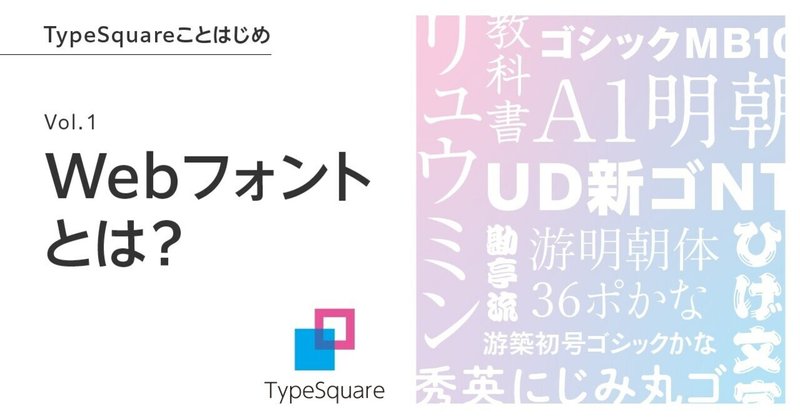
Webフォントとは? 「TypeSquare」ことはじめ
日々の情報収集やコミュニケーション、そしてショッピングや公的サービスの手続きなど、私たちの生活においてインターネットは必需品となりました。朝から晩までスマートフォンを見ていることも珍しくない今、Webサイトにおけるフォントは、サービスの印象や情報の伝わりやすさを決める要素として大きな役割を果たしています。
2021年、株式会社モリサワが提供するWebフォントサービス「TypeSquare」は、リリースから10年目を迎えました!そこでモリサワnote編集部では、もっとみなさんにWebフォントの素晴らしさを知っていただきたく、「TypeSquare」についてお伝えしていきたいと思います。
第1回目は自己紹介として、これまで日本語Webフォントが歩んできた道と、知っておいていただきたいことをご紹介します。
1.そもそもWebフォントって?
通常ウェブサイトは、パソコンやスマートフォンなどの端末へインストールされているデバイスフォントの中から、CSS(スタイルシートと呼ばれる、ウェブサイトの見た目を決める言語)で指定されたフォントを表示しています。
対してWebフォントは、サーバからフォントファイルを配信し、そのフォントを使ってウェブサイトを表示する仕組みになっています。つまり、指定されたフォントが端末にインストールされていなくても、デザイナーや開発者の指定する書体が表現できるのです。
2.Webフォントの歴史
1990年代後半、CSS2にウェブブラウザへのフォント自動ダウンロード、および一時的にアクティブ化を可能とする「@font-face」規則が導入されたことで、Webフォントの仕組みが完成しました。
しかし、当時はInternet Explorer4のみで使える、Microsoft社 独自仕様のフォントフォーマットEOT(Embedded OpenType)にしか対応できず、利用は限定的なものでした。
2000年代に入り、Firefox・Safari・Google Chromeなど、新しいウェブブラウザが次々と登場。TrueTypeやOpenTypeといった一般的なフォントフォーマットが「@ font-face」規則に対応できるようになりました。
これにより、欧米ではWebフォントの利用が増加!2000年代後半には、Typekit(現在のAdobe Fonts)やGoogle Web FontsなどのWebフォントサービスも登場し、どんどん普及が進みます。
そして、欧米より数年遅れをとることの2010年。ついに国内初の日本語対応Webフォントサービスが登場し、国内でもWebフォントサービスが少しずつ普及していきました。
3.日本語Webフォントが歩んできた道
では、10年目を迎える「TypeSquare」の進化とともに、日本語Webフォントがこれまで歩んできた道を振り返ってみましょう。
先ほど“欧米より数年遅れをとることの”とお伝えしたのには、日本語ならではの理由がありました。みなさんもお気づきかもしれませんが、日本語の書体は、漢字・ひらがな・カタカナと文字数が非常に多く、欧文書体に比べてデータサイズが数MBと格段に大きくなってしまうハンディがあります。
※ちなみに、モリサワフォントで提供している文字セットの最多収録文字数は『23,058文字』もあります!
よって、サービス開始当初の日本語Webフォントはデータサイズが大きく、ネットワークに負荷がかかり、ウェブサイトの表示に時間がかかってしまっていました。このタイムラグを解消するため、技術者たちは年々サービスを進化させます。
今では、表示に必要な文字だけをダウンロードする「ダイナミックサブセット」方式を利用し、配信するフォント自身の軽量化に成功!多くの場合、ファイルサイズは画像数枚分に収まるようになりました。
読み込み速度が向上したことで、通信速度が安定しない外出先やポケットWi-Fiなどの環境下でも、快適にウェブサイトを表示できます。現在では、更にデータサイズが小さくなった専用のフォントフォーマットWOFF(Web Open Font Format)で配信しているため、さらに表示速度が向上しました。
4.「TypeSquare」が得意なこと
ここからは、日本語Webフォント「TypeSquare」を利用するメリットをご紹介します。
■あらゆるニーズに応えます!豊富な書体ラインナップ
なんといっても、モリサワが提供する1,000書体を超えるフォントを、あらゆるデジタル端末で使えること!
一般的な明朝体やゴシック体はもちろん、デザイン書体や、かな書体、装飾書体、UD(ユニバーサルデザイン)書体に加え、欧文書体、中国語、韓国語など豊富な書体ラインナップを用意しています。多くの印刷物をはじめ、テレビのテロップやサイネージ、家電製品、ゲームなど、さまざまなシーンで利用されているモリサワフォントを、そのままウェブサイトでも使用可能。印刷物からデジタル端末まで、ブランドの世界観に一貫性を持たせられるのは魅力的ですよね。
では、Webフォントによってどれだけ印象が変わるのかを、実際に体験していただきましょう。
まずこのウェブサイトは、PCのデバイスフォントで表示させていますが、
全く同じデザインのウェブサイトをWebフォント(下は「解ミン 宙」)に変更すると、印象がガラッと変わります!
つまり、ウェブサイトの世界観を表現する上でも、書体選びはとても重要な役割を果たしているのです。
■ウェブサイトの制作・更新フローがラクに
これまでは、見出しやボタンの文字に好みの書体・効果を指定したい場合、画像を個別に作成していました。そのため、文字に変更があった場合は都度画像を作り直し、再度サーバへ上げなおす必要があったのです。
Webフォントなら使いたいフォントを指定して、通常のテキスト同様に文字サイズの調整やCSSによる効果を設定するだけでOK。急な文字修正が生じても、画像を作り直す手間が解消されます。
■拡大してもクリアで美しい文字
高解像度化が進むスマートフォンやタブレットでは、画像化された文字は画面をピンチアウトさせた際にぼやけて表示されることも。しかしWebフォントを使うことで、画面を拡大しても文字はクリアで美しさもキープ。ウェブサイトの仕上がりに大きく差がつきます。
■情報の検索性・活用性がアップ
ウェブサイトの検索性を高めるためには、画像で作成したタイトルや見出しは、その情報をalt属性としてタグに記述することが推奨されています。
しかし、Webフォントを指定した文字は完全なテキストとして扱われるため、手間のかかるalt属性の設定作業は不要。さらには自動翻訳や音声読み上げなどの機能とも連携しやすくなり、アクセシビリティが向上することでSEO対策にも繋がります。
■レスポンシブデザインにも最適!
ウェブサイトは、パソコン・スマートフォン・タブレットなどあらゆる端末で閲覧されるため、大小さまざまなスクリーンサイズや解像度に対応できなければなりません。
その制作手法のひとつであるレスポンシブデザインは、異なる画面サイズに応じてレイアウトが自動的に調整されます。よって、文字組が多様に変更される手法とも相性ピッタリ。
また、Googleが推奨する
・スマートフォンに対応した「モバイルフレンドリーなウェブサイト」が構築できる
・サイト構造がシンプルになる
・各デバイスのURLを統一できることでリダイレクトが不要になる
ことから、SEOの効果も期待できます。
5.採用時にネックとなりがちなこと
多くのメリットがありながらも、今も以下のような「日本語Webフォント利用時のデメリット」の印象があり、採用する際にネックとなってしまうケースがあるようです。
・フォントのデータサイズが大きく、ウェブページの表示速度が遅くなる。
・ブラウザによっては、文字のベースラインがズレることもある。
・日本語に対応したWebフォントが少ない。
・費用が発生する。
表示速度に関しては、「TypeSquare」は前述のとおり日々表示速度の向上に取り組んでいて、10年前のリリース当時と比べると格段に速くなっています。文字のベースラインに関しては、この事象が語られていた当時からブラウザも進化を遂げ、昨今、シンプルな文字組の体裁におけるズレはとても少なくなりました。
フォント数に関しては、「TypeSquare」にはモリサワが提供する1,000書体を超える豊富なフォントラインナップを揃えています。そして費用に関しては、「TypeSquare」を採用することでデザイン性や操作性といったデジタルサービス全体のクオリティが上がり、費用以上のメリットを感じていただけると自信を持っています。
6.速く優しく美しいウェブサービスへ
ウェブサイトは大部分を文字情報が占めていて、スマートフォンサイトではディスプレイに文字のみが表示されているケースも多いですよね。よって、モリサワの美しいフォントを使うことで、ウェブサイトの印象が大きく変わることも実感いただけると思います。
また、技術の進化によってスピーディな表示も可能となり、検索性やアクセシビリティの観点からユーザーにとって優しく、かつ、多忙なデザイナーや開発者の作業効率化にも一役買うことができます。
使い手にとって、そして作り手にとって“速く優しく美しい”ウェブサービスを提供できる「TypeSquare」に、これからもぜひご注目ください。今後モリサワnote編集部では、「TypeSquare」の採用事例やテクニカルな情報もご紹介していきますので、楽しみにしていてくださいね。